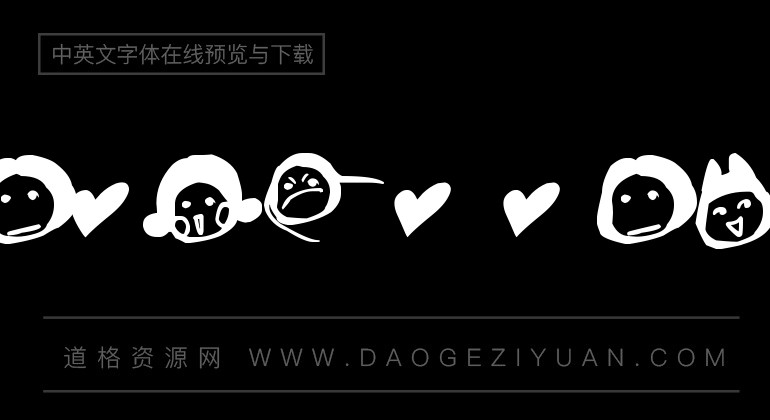
Simplesymbol 字体是一种简单的符号字体,它具有简洁、灵活、清晰的设计,可以用于各种应用场景,尤其是用于网站设计和图标设计。Simplesymbol 字体拥有多种符号,可以用来表达不同的情绪和概念,可以更好地支持设计师的创意表达。Simplesymbol 字体是一款开放源代码的字体,可以免费下载,可以用于个人和商业项目。内容介绍
Simplesymbol是一款非常不错的手写艺术字体,具有很好的视觉感,适合于文化类的宣传设计、商业类品牌的广告和产品包装设计以及个性化文字排版等较多场景。